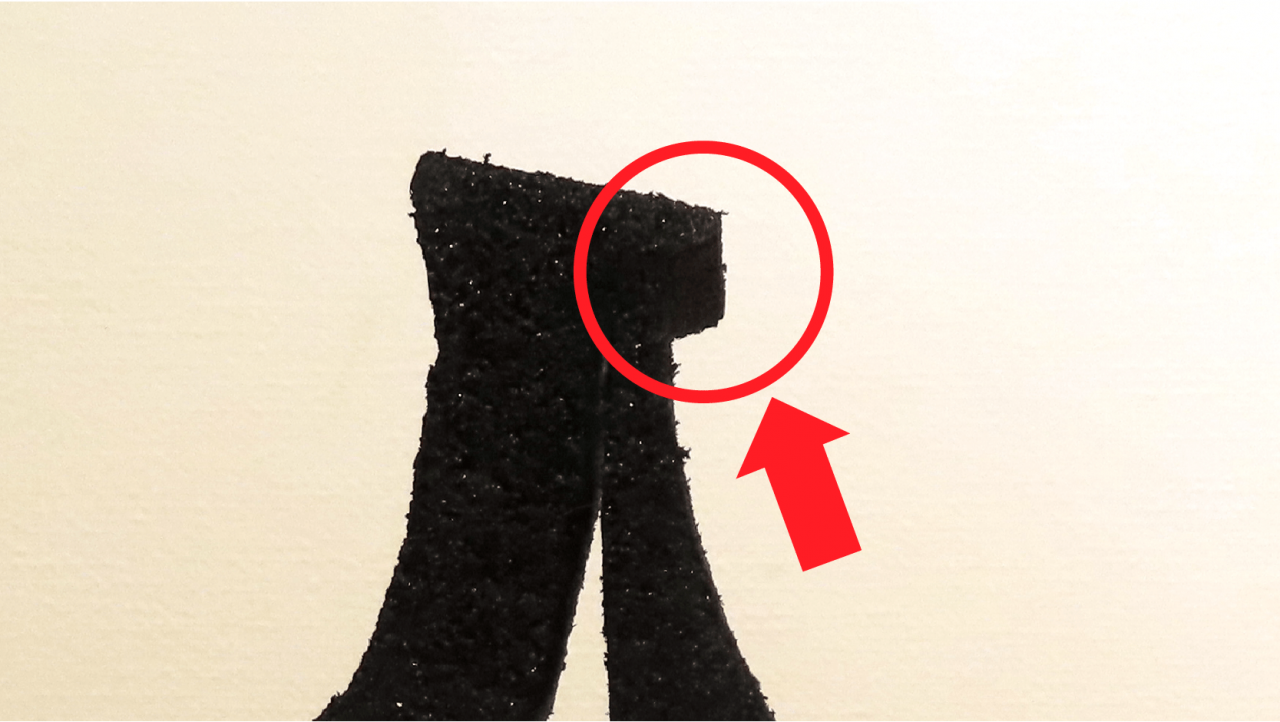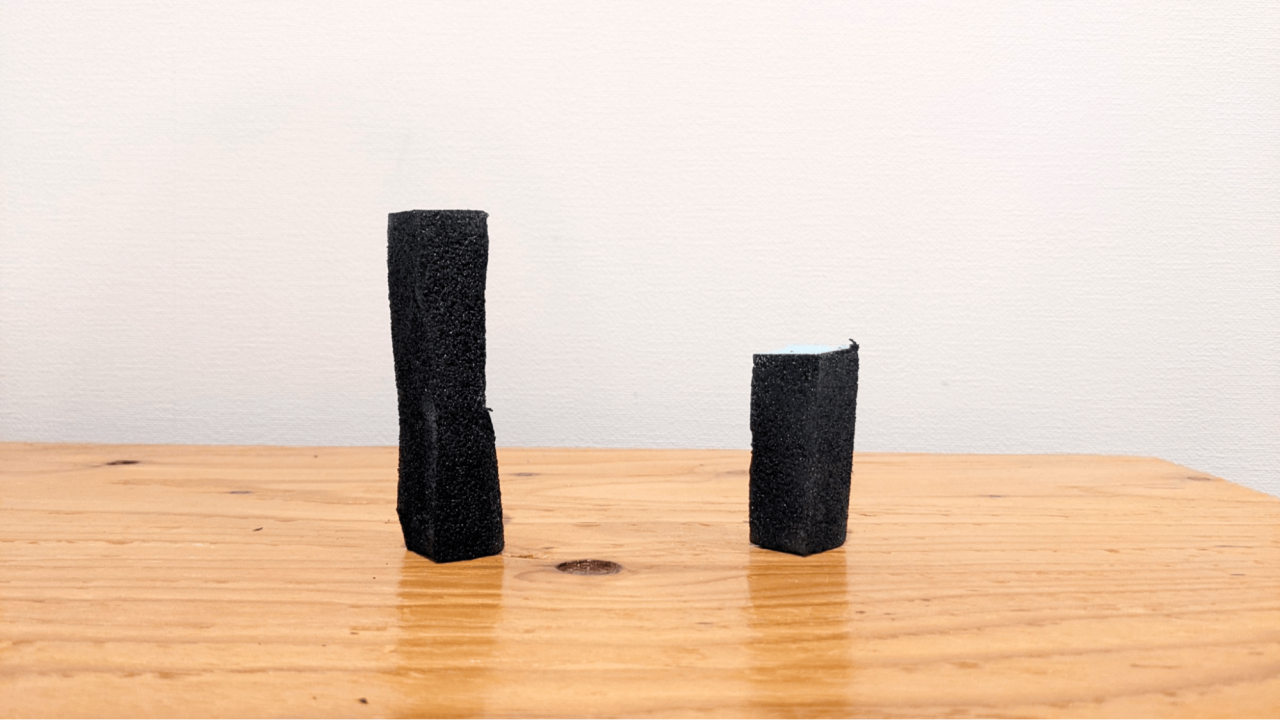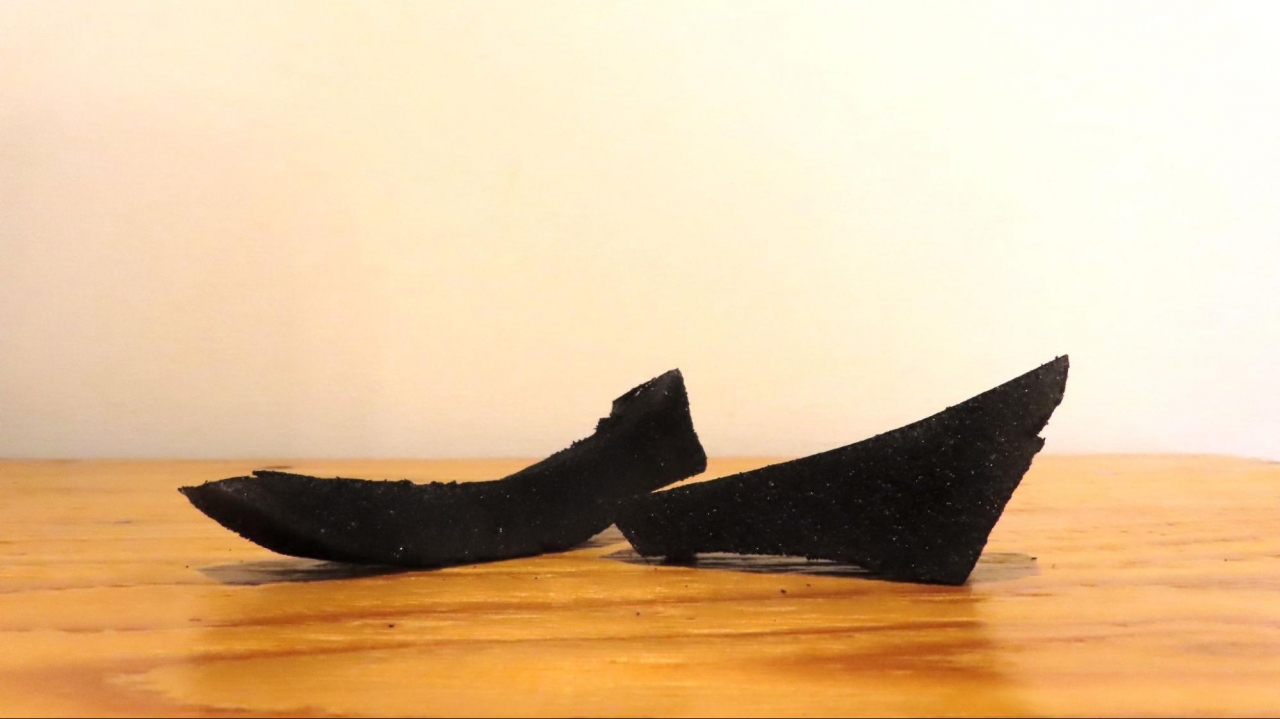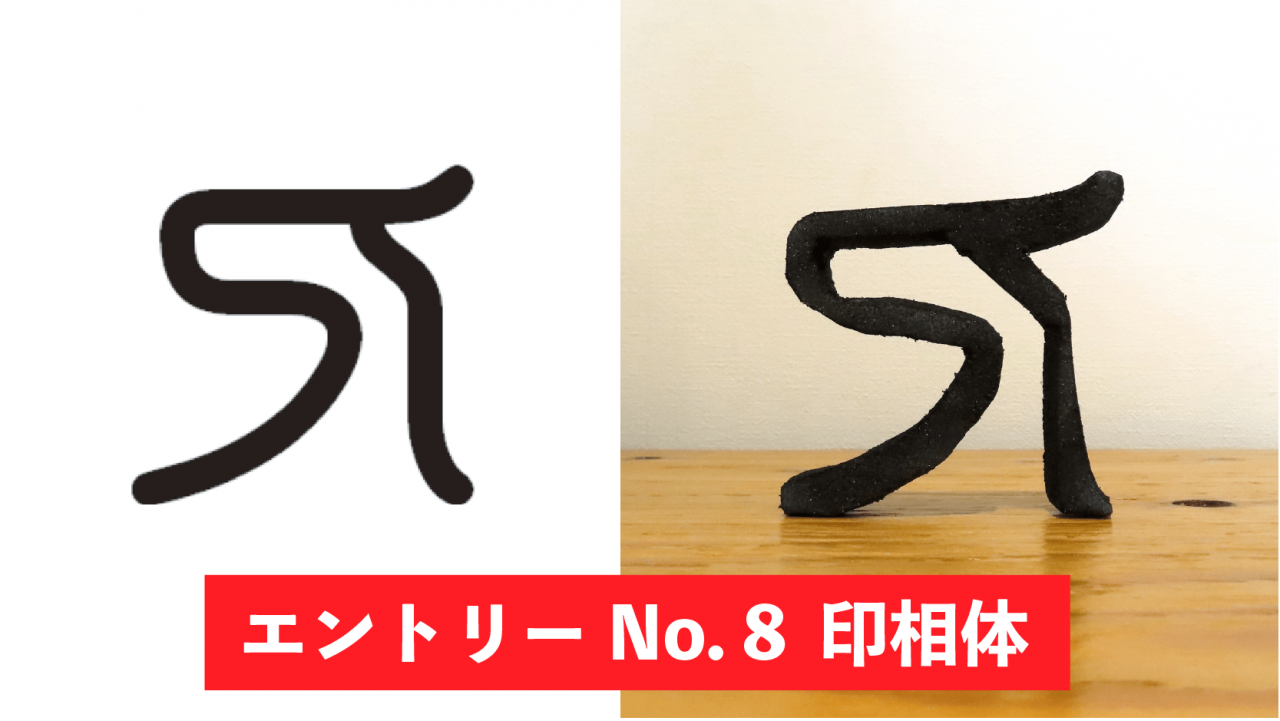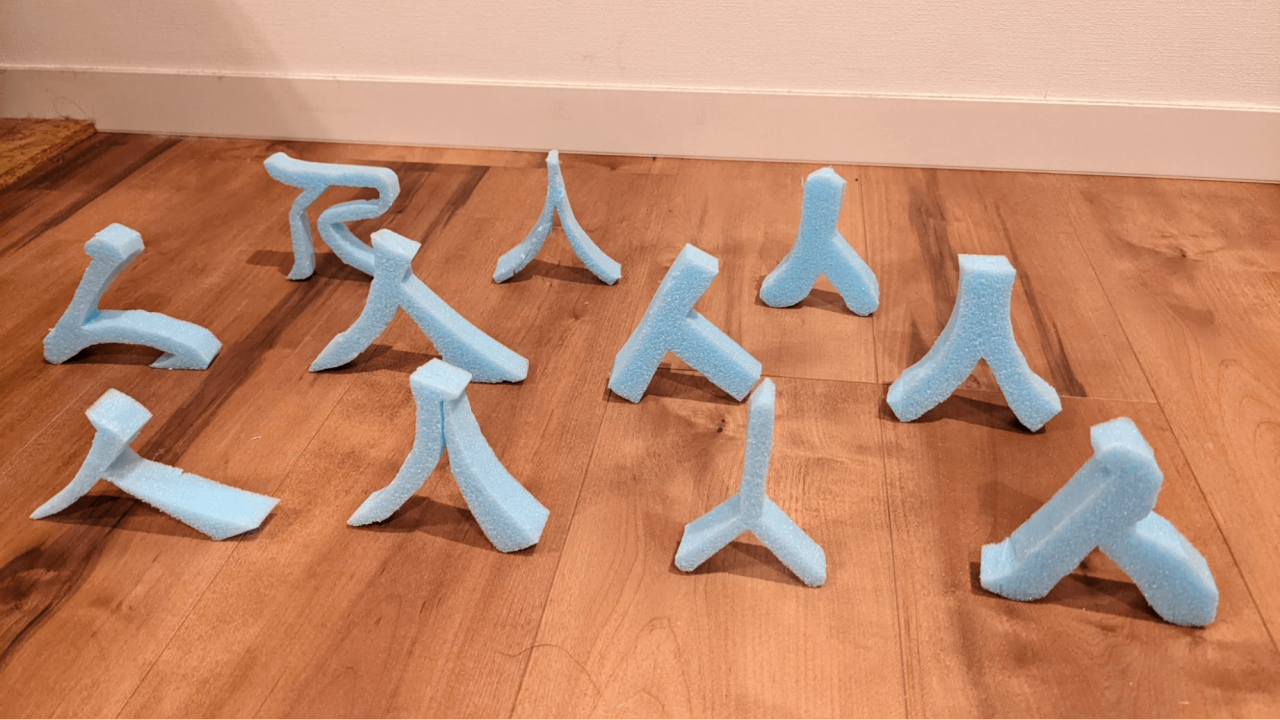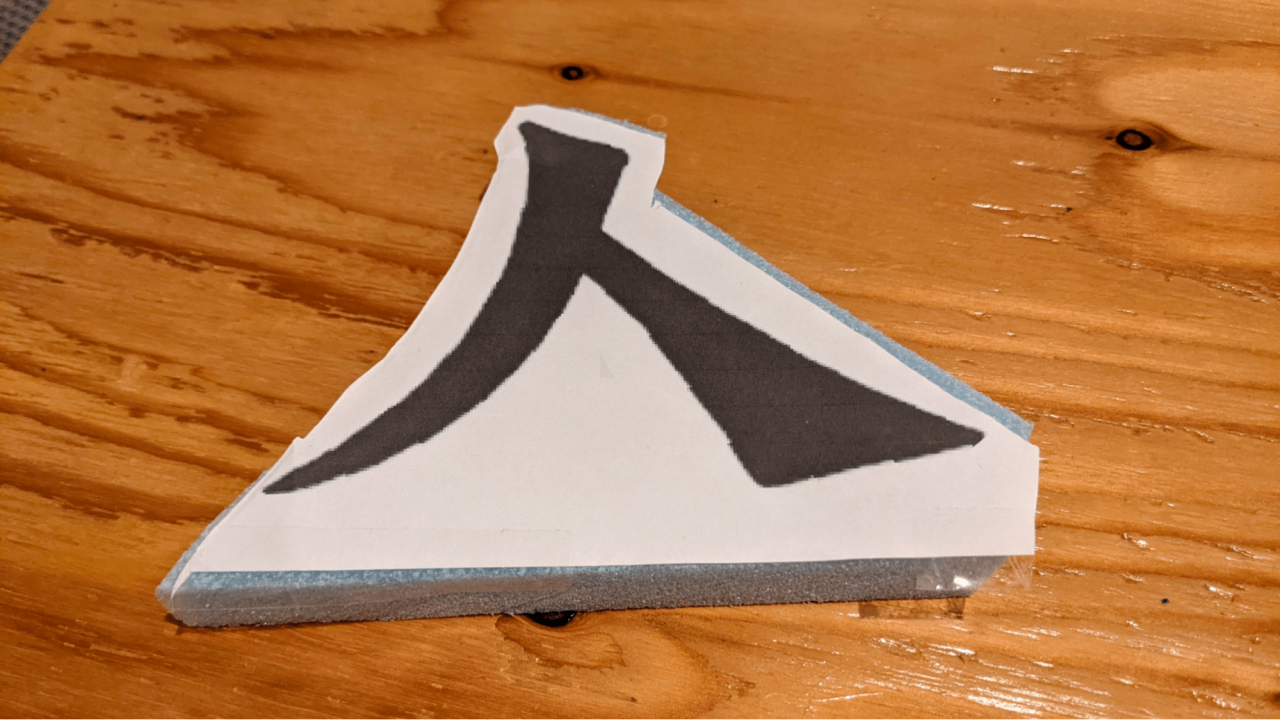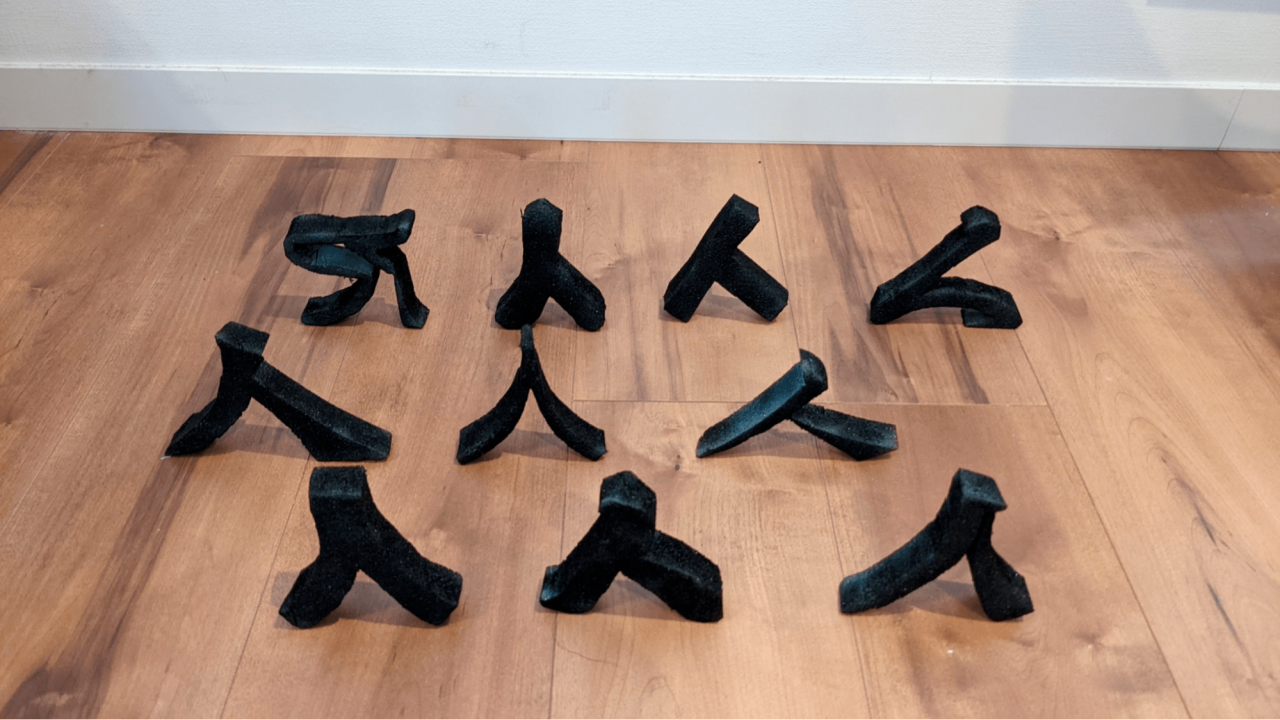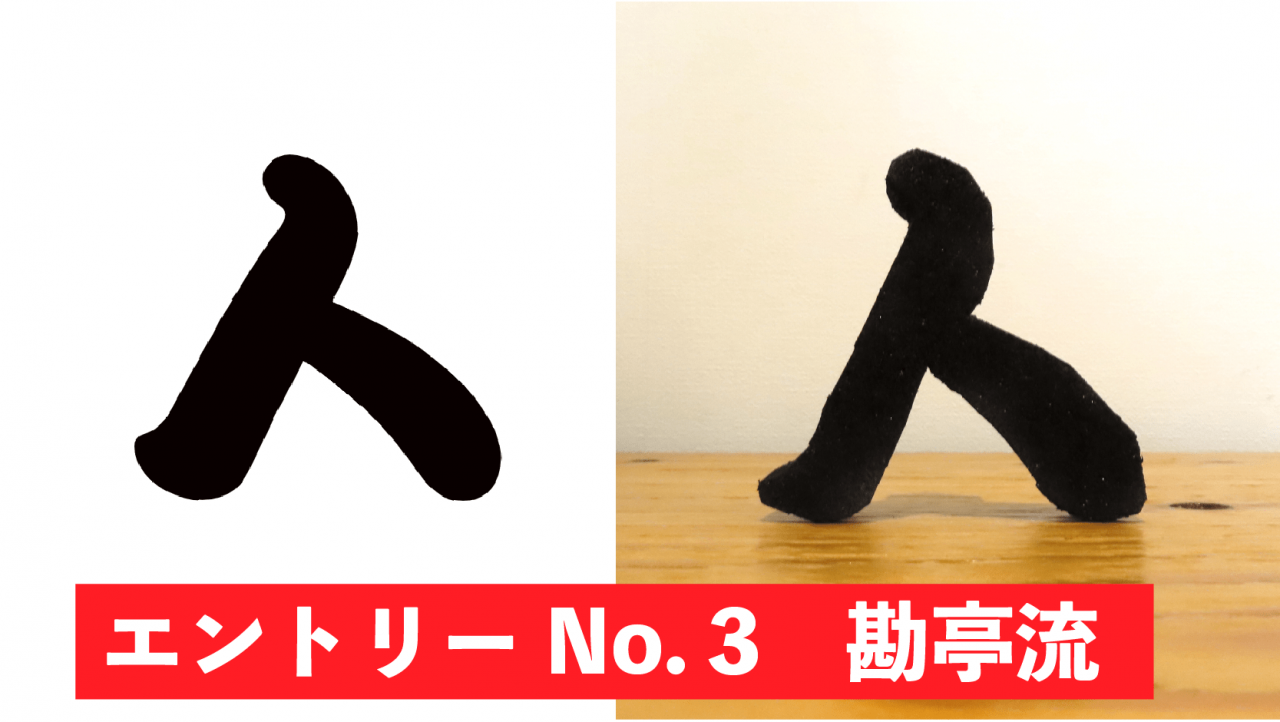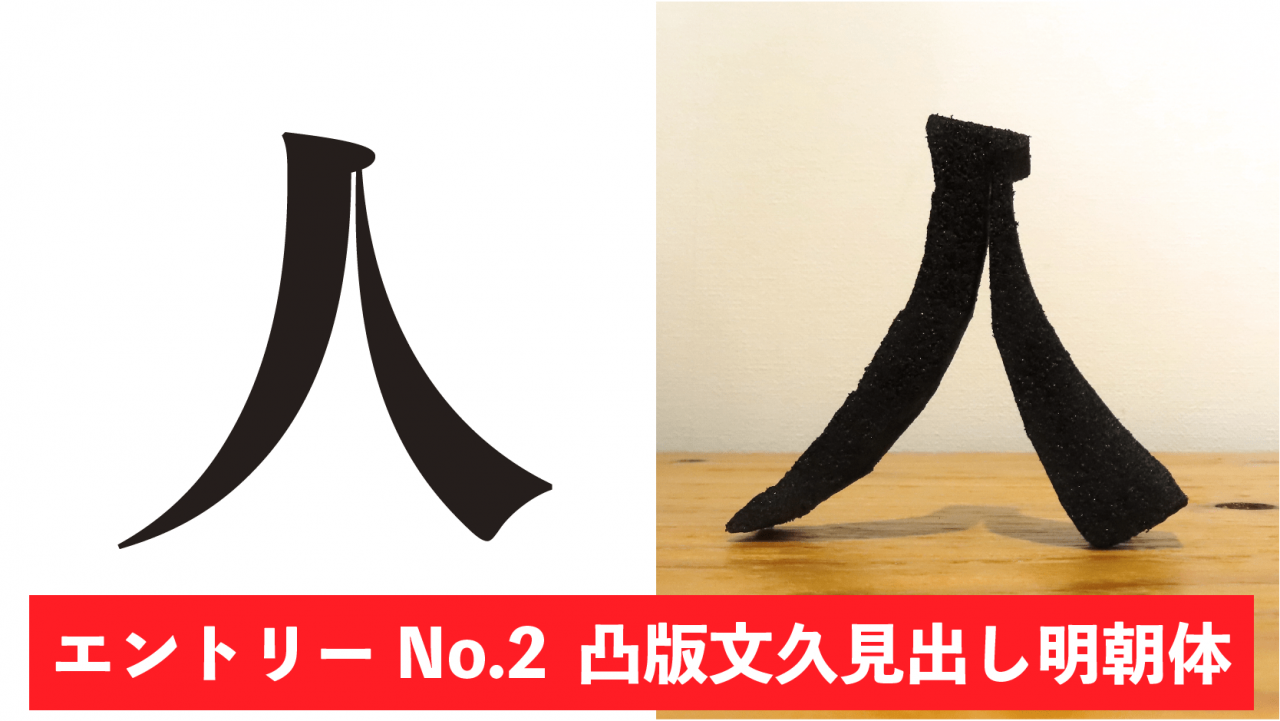
はりきりすぎて大量の「人」を作ったせいで、全部を紹介しきれなかった。しかたないので、ここでおまけの「人」を紹介する。
教科書体は特に最難関で、作っているときから「あなたたちは本当に支え合えるのか?」と聞きたくなるぐらい不安定な「人」だった。
人と人が支え合っている話をするときは、教科書体よりポップ体なのだ。ぜひ、今後支え合いの話をするときは参考にして欲しいと思う。
「人という字は、人と人が支え合ってできている」という言葉がある。
しかし、実際の人の支え合い方には差がある。細い明朝体の「人」は、かなりぎりぎりでお互いを支えているように見えるし、逆に太い筆文字の「人」は、ガッツリホールドしていて息ピッタリな気がする。
いろいろな「人」がある中で、一番「人と人が支え合っている人」はどれなのか。実際に「人」を作って確かめたい。
人という字は、人と人が支え合ってできているという。
でも、現実にはいろんな「人」があるので、必ずしも支え合っているとは限らない。
一番「人と人が支え合っている人」はどれなのか。
その答えを探るべく、物理的にたくさんの「人」を作って確かめてみることにした。
またたくまに、黒い人だかりができた。これで下準備は万全だ!
今回は、次の2つのルールで人の支え合い方をチェックする。
まずはとにかくやってみよう。エントリーNo.1はこの「人」だ。
龍門石碑体は、書道などでお手本にされることもあるという文字だ。そのせいか、いかにも見た目が「人」っぽい。
「人という字を思い浮かべて」と言われたら、だいたいの人がこんな感じの「人」を思い浮かべるはずだ。
そんな王道派ともいえる龍門石碑体の「人」だが、本当に支え合っているのだろうか。
人の支え合っている部分に、カッターで亀裂を走らせてみる。
お互いをばらばらにした途端、2人とも力なくその場に倒れ込んでしまった。
やはり、人という字は常にお互いを支え合っていないとダメなのだ。
余裕とまではいかなかったが、2人が支え合うことで、ちゃんと「人」が立つことができた。
どちらが欠けてもうまくいかない。お互いがお互いを支え合っている、これぞまさに「人」である。
しかし、勝負はこれだけではない。どんな障害でも2人は乗り越えられるのか、揺れを与えてチェックする。
いい揺れの与え方がよくわからなかったので、とりあえずテーブルを叩きまくったらすぐに崩れ去ってしまった。
龍門石碑体の「人」は、障害を乗り越えられるほど支え合ってはいなかったらしい。
この調子で、他の「人」もどんどんチェックをしていこう。
「凸版文久見出し明朝」は、最近トレンドのフォントである。使いやすくてちょっとかわいらしいので、バナーや装丁で見かけることが増えてきた。
いわばフォント界のホープだが、ちゃんと人と人は支え合っているのだろうか?
すっくと立った。こんなに不安定そうなのにきちんと支え合っているなんて、なんだかちょっと感動する。
凸版文久見出し明朝で特に感動するポイントは、上にちょっとだけある「でっぱり」だ。
正直、これがなければかなり支え合えない人だと思う。
お互いがなんとか工夫をしながら、必死にお互いを支えている感じがすごくいい。
机を叩くと、0.5秒ぐらいでもろくも崩れ去っていった。やはり、もともとの太さがないと「人」は衝撃に耐えられないらしい。
続いては、江戸っぽい雰囲気を出したいときに絶対に出てくる勘亭流の「人」である。
見た目は人情あふれる「人」に見えるが、実際のところどうだろうか。
こんなに人情味がありそうなのに、揺れがきたらすぐにお互いを見捨ててしまった。せちがらい世になったものだ。
しかたがないので、相撲文字に期待する。
相撲といえば足腰が大事だ。しかも、相撲のとっくみあいはかなり「人」の形っぽい。
これは期待が持てそうだ。がんばれぼくらの相撲文字!
さすが天下の相撲文字! 最後は崩れてしまったものの、ぎりぎりまでがっつり組み合う最高の支え合いを見せてくれた。やっぱり最後は人と人の支え合いだ。
ここまで手書きっぽい「人」ばかりを見てきたが、ここでゴシック体の「人」にも出てもらおう。
ゴシックの「人」は、正直作るかかなり迷った。なぜかというとコレである。
たぶんなのだが、「人と人は支え合っている」と最初に言いだした方は、筆で描いた「人」をもとにして言ったんだと思う。ゴシック体のことは、なにも考えてなかったはずだ。
ちょっと亀裂は入ったものの、揺れにも負けないゴシック体。ゴシック体でも、人は支え合うことができるのだ。
もうひとつ、忘れちゃいけないのがポップ体だ。
ちょっと軽薄なイメージがついてしまっているポップ体だが、人と人が支え合っているのなら、ファンを増やせるかもしれない。
圧倒的な支え合いだ。バラバラになっても立ち上がり、2人になっても立ち上がる。
倒れるまでテーブルを叩き続けてみたものの、全然崩れる気配がないので最終的に私が負けた。
いまだかつて、ここまで支え合う「人」がいただろうか。ポップ体、圧巻の支え合いである。
最後は、変わった「人」を見ていこう。
できるだけ早く文字を書くための崩し文字、それが草書体である。
崩し文字だけあって、ゴシック体とも一味違った「どこで切っていいのかわからん」感がただよっている。
人というより「ろ」になった。こんな「ろ」のような人は初めて見た。
草書体の「人」は全然支え合っていなかった。この世には、やはりいろんな人があるようだ。
他のどんな「人」とも違う、謎の風格ただよう印相体。
見たことがない人も多いと思うが、簡単にいえば「ハンコのための文字」である。
かなり支え合い感のあるフォルムに見えたが、その特殊さが裏目にでたのか、ガッツリ支え合うことはできなかった。「人」は見た目によらないのだ。
いろんな「人」の支え合いを見てきたが、結果を一覧でまとめてみる。
ということで...
一番人と人が支え合っているのは、ポップ体の「人」だった。
特に「切り離されても立ち上がる」「どれだけ障害があっても支え合う」という強さを見せてくれたのは、たくさんの「人」の中でもポップ体の「人」だけだ。
今後もし「人という字は、人と人が支え合ってできている」という話をするときには、ポップ体の「人」を使うことをおすすめしたい。
教科書体は特に最難関で、作っているときから「あなたたちは本当に支え合えるのか?」と聞きたくなるぐらい不安定な「人」だった。
人と人が支え合っている話をするときは、教科書体よりポップ体なのだ。ぜひ、今後支え合いの話をするときは参考にして欲しいと思う。